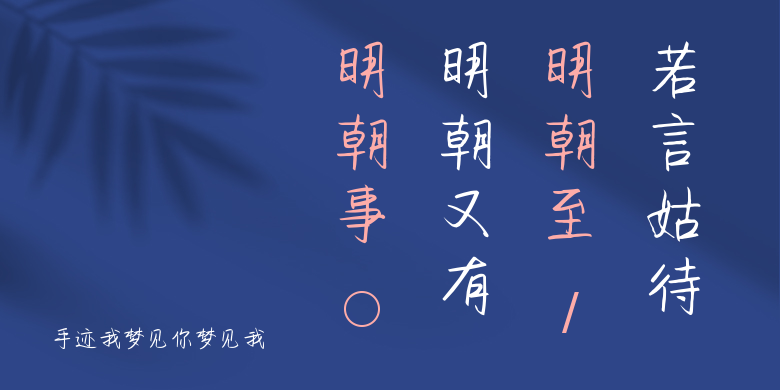
手迹我梦见你梦见我
手迹我梦见你梦见我,这款字体结构工整、笔画清晰,兼顾美观与易读性,适用于标题、正文、海报、包装、LOGO 等多种场景。字形优雅稳定,风格百搭耐看,适配日常排版与创意设计,让文字呈现更舒适、更具质感。手迹我梦见你梦见我一笔一画,皆是细节,以均衡的比例、流畅的线条打造舒适视觉体验,字形端正大气,风格简约现代。无论是商业设计、品牌宣传还是日常排版,都能轻松驾驭,让文字更有格调与力量。手迹我梦见你梦见我字体下载。